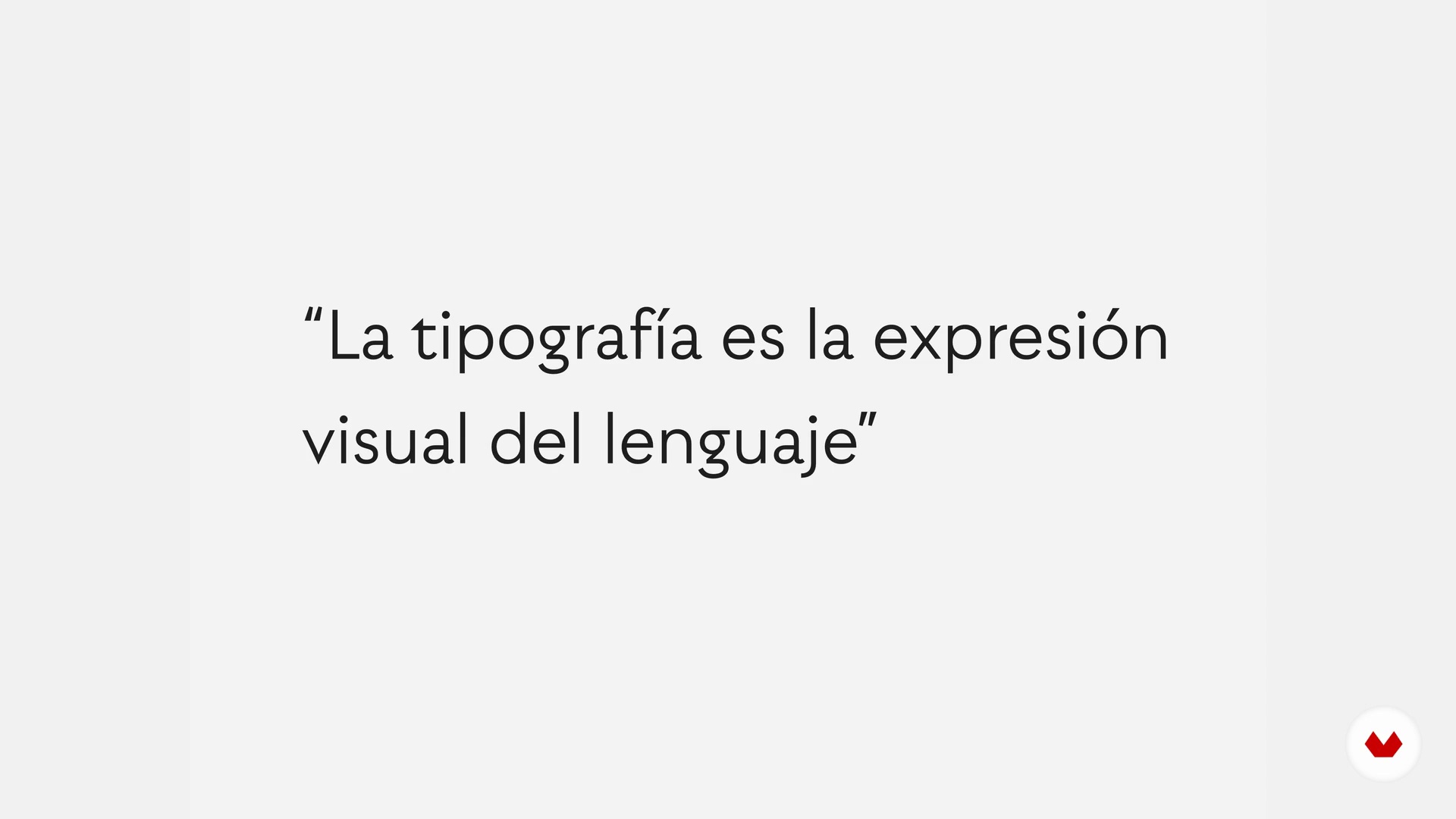
Qu'est-ce que la typographie?
À propos de la leçon : Qu'est-ce que la typographie?
“Afin de mieux se comprendre, nous allons voir les différentes définitions et distinctions du terme typographie.”
Dans cette leçon, Latinotype aborde le sujet : Qu'est-ce que la typographie?, qui fait partie du cours Domestika en ligne : Principes élémentaires du design typographique. Apprenez à créer votre propre alphabet modulaire avec Adobe Illustrator.
“Avant de continuer, nous allons voir ce qu'est la typographie, il est important que nous comprenions les définitions et les différentes distinctions de termes. Qu'est-ce que la typographie ? Nous avons la première définition qui est un concept global. Ce serait : « La typographie est l'expression visuelle du langage. Cette phrase est parvenue à nos oreilles par le père de la typographie latino-américaine, Rubén Fontana, fondateur du magazine éteint tipogGráfica ou TPG, l'un des magazines hispanophones les plus importants qui a été distribué de l'Amérique latine au monde. En outre, il a fond...”
Latinotype, fondée par Luciano Vergara et Daniel Hernández, est la première fonderie de types au Chili. Fondée en 2011, une équipe compte aujourd'hui une équipe de conception, de gestion et de marketing composée de professionnels de différentes régions du monde, ainsi que d'une vingtaine de collaborateurs nationaux et internationaux. Avec plus de 8 ans d'expérience, ils sont aujourd'hui leaders sur le marché du commerce de détail, développant des projets utilisés par les grandes marques du monde entier.
Son travail peut être trouvé dans des publications internationales telles que Yearbook of Type, d'Allemagne; Caractère Latino, d'Espagne; Magazine UC Design ou magazine Slanted, entre autres. En outre, ils ont donné des ateliers et des conférences au Brésil, au Chili, en Argentine, au Pérou, en Colombie, au Mexique, au Guatemala et en Uruguay.